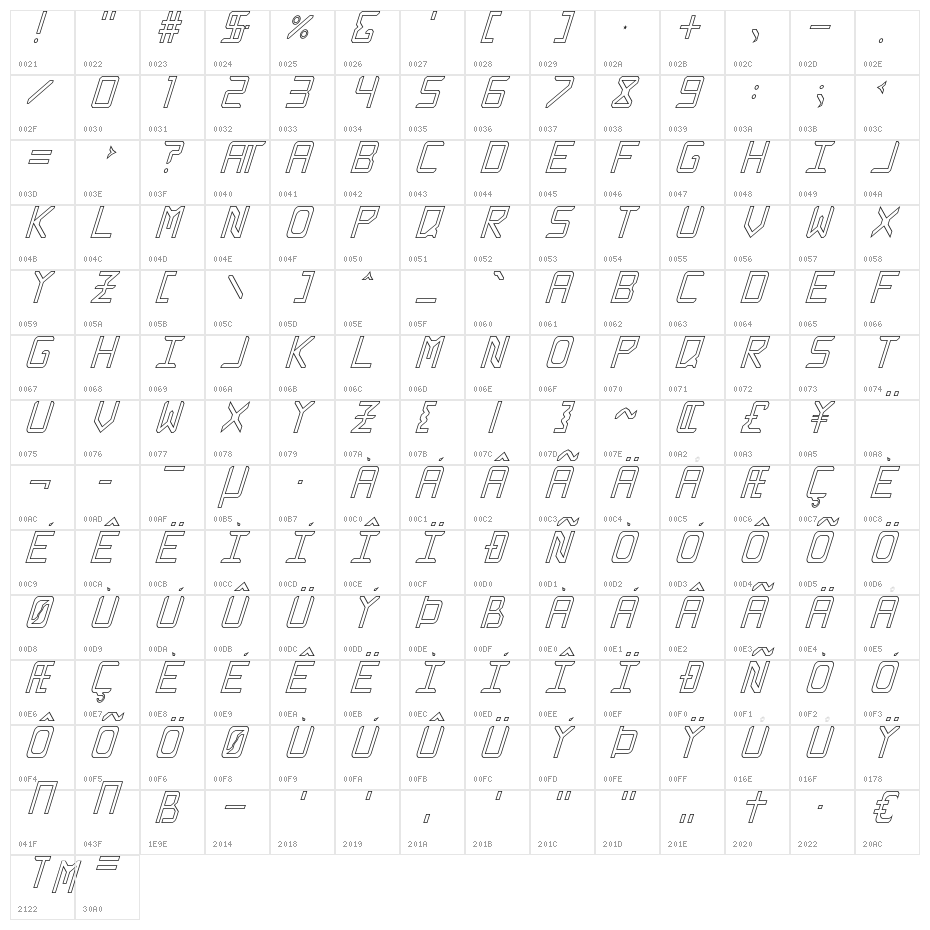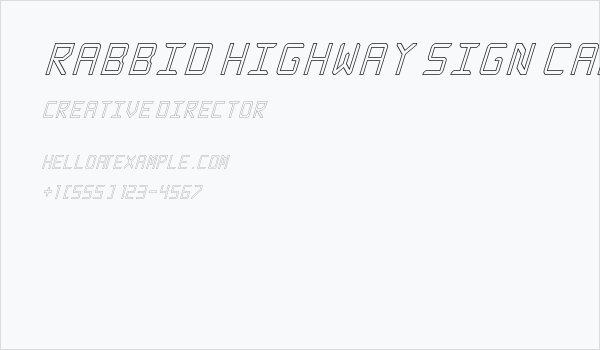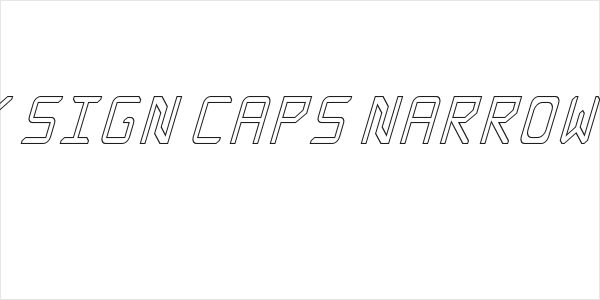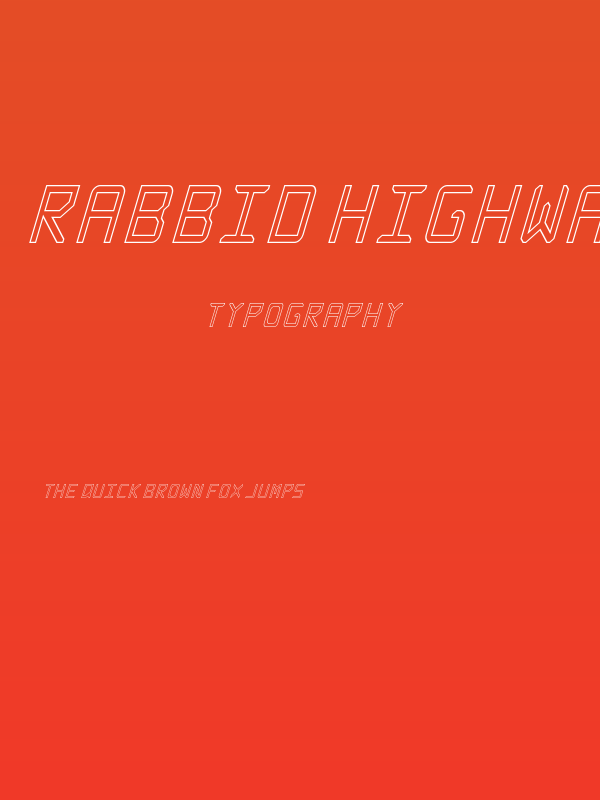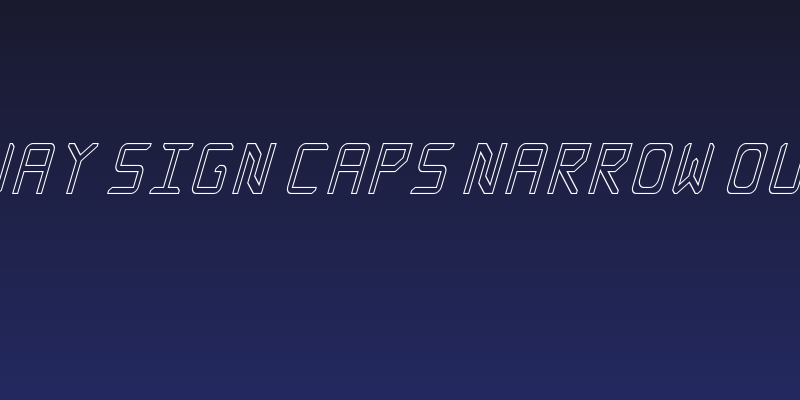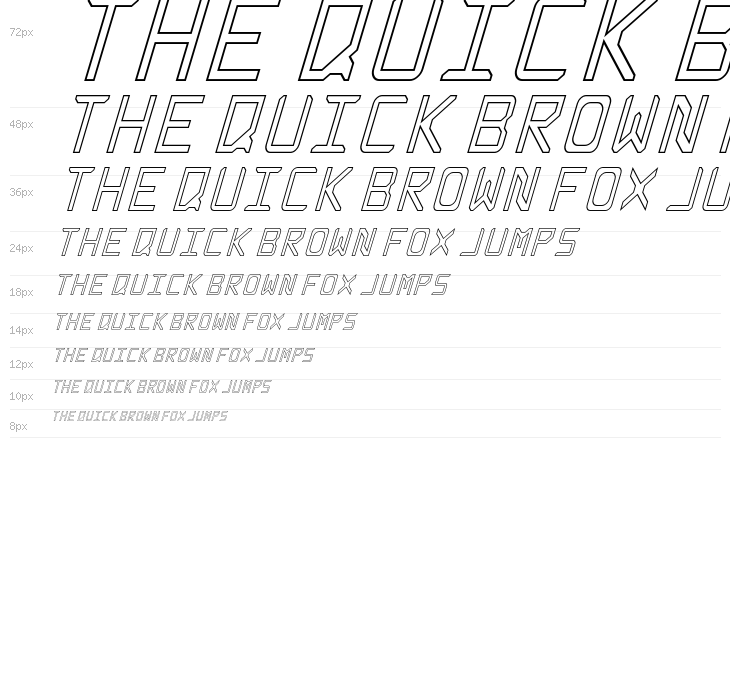
Rabbid Highway Sign Caps Narrow Outline Italic Font
✎ Outline
| Categorie | Outline |
| Caso d'uso | Headlines, Logos, Signage |
| Progetti proposti | Ideal for futuristic designs, tech-related branding, signage, and posters that require a standout and modern aesthetic. |